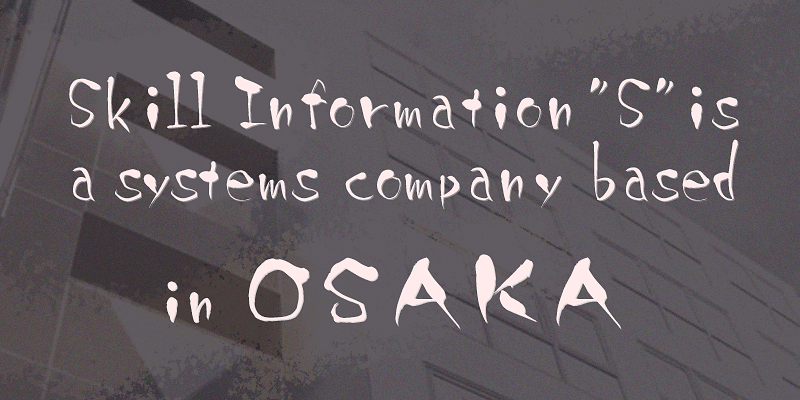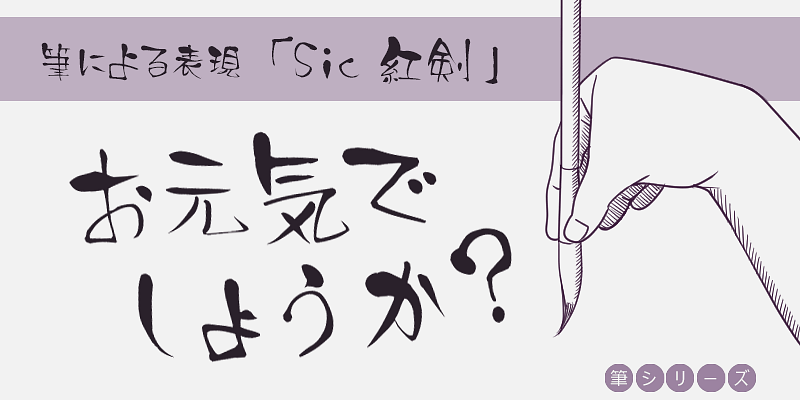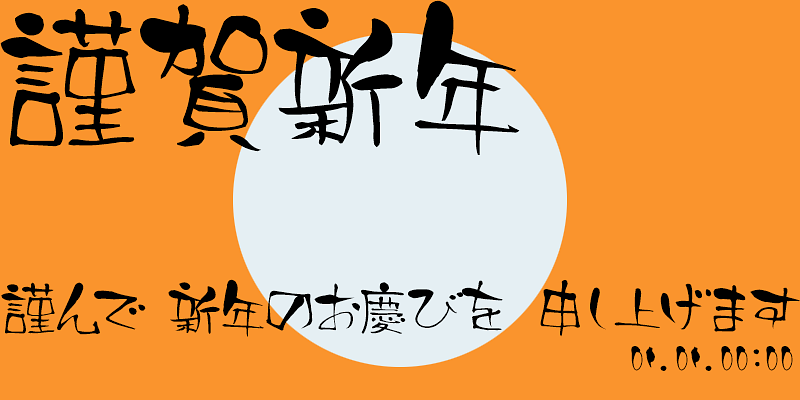
宮城英生氏の手書き筆文字書体フォントは、力強さと繊細さを併せ持つ独特の筆致が特徴です。太字は力強く存在感があり、細字は繊細で味わい深い表情を生み出します。自然な筆圧の変化が温かみを感じさせ、可読性も優れています。和の趣を活かしつつ現代的なデザインにも調和し、居酒屋のメニューやポスター、YouTube のサムネイルなど幅広い用途で活躍。宮城氏ならではの情緒あふれる筆文字が、力強さと温もりを作品に加えます。
スキルインフォメーションズはヘルスケア関係のソフトウエア開発を中心とする会社ですが、2007 年にフォントシステムの開発を手掛けていたテクノアドバンス社と事業提携し、フォント事業部を開設しました。